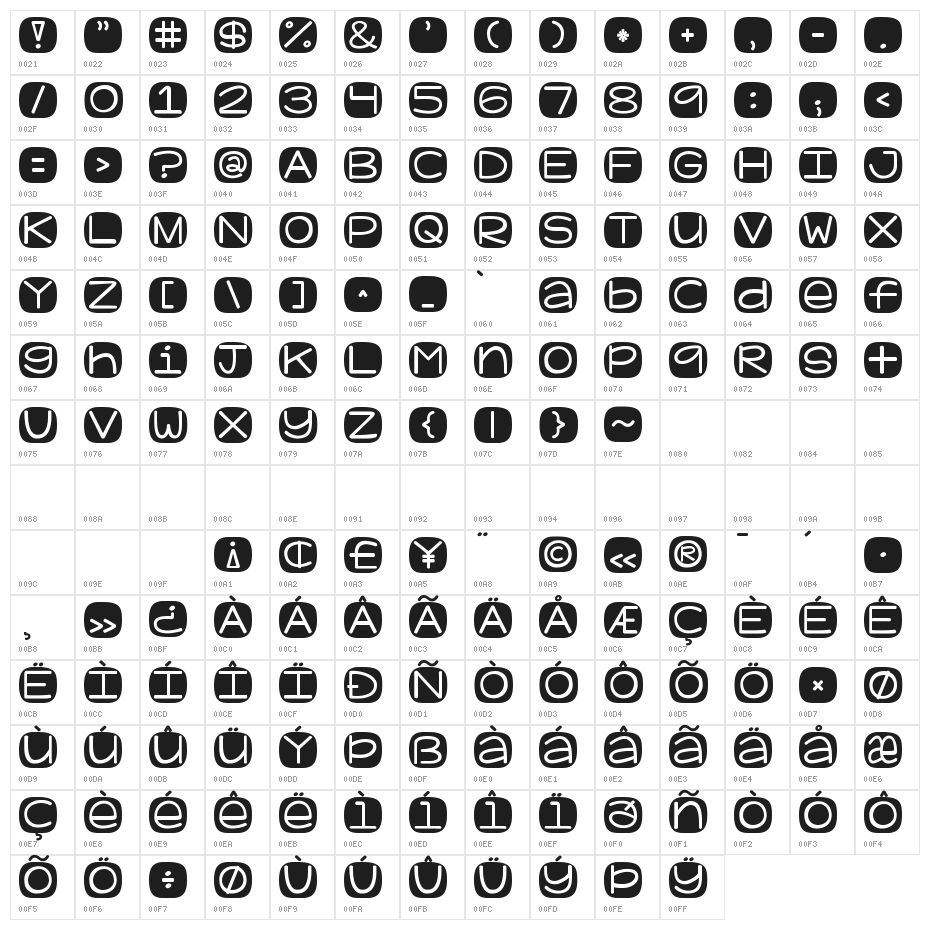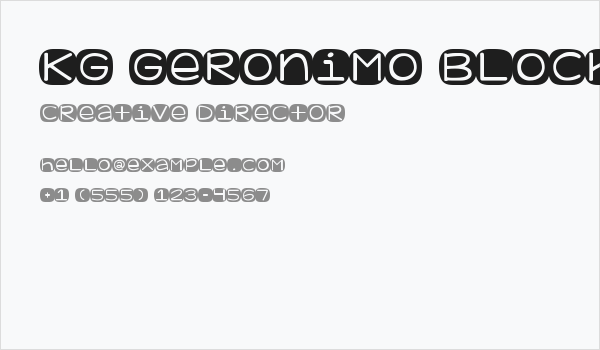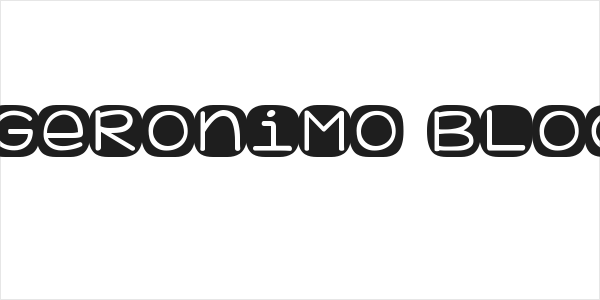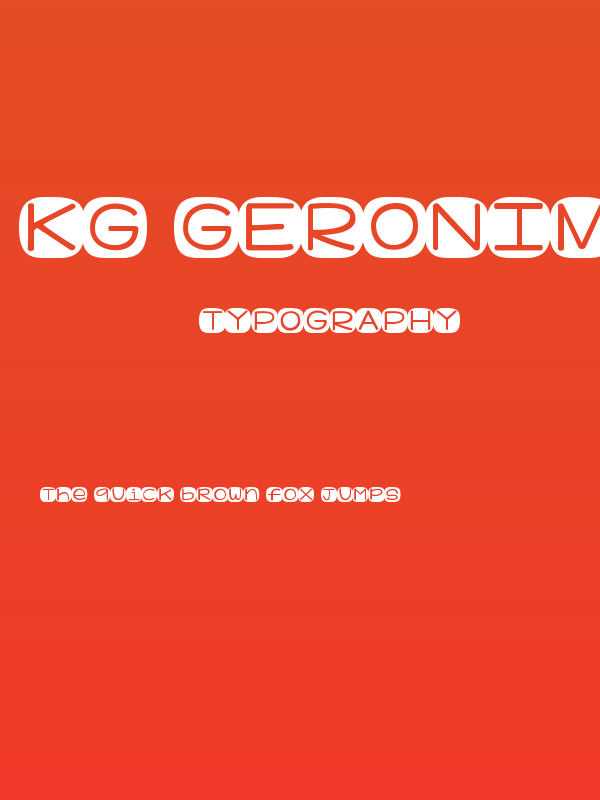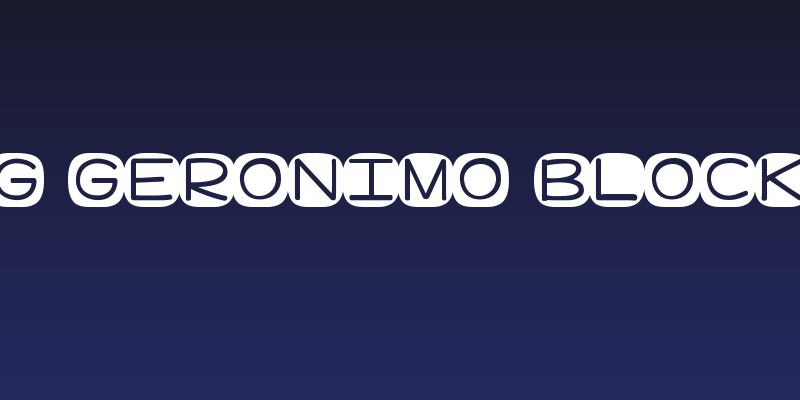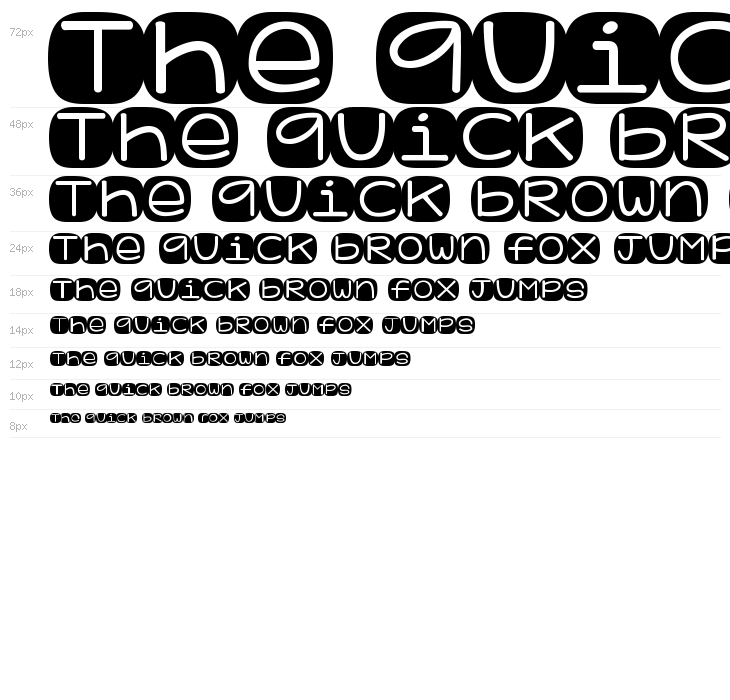
KG Geronimo Blocks Font
| Stile generale | Retro, Playful |
| Caso d'uso | Logos, Posters, Headlines |
| Progetti proposti | Ideal for children's books, playful branding, posters, and retro-themed designs. |
KG Geronimo Blocks